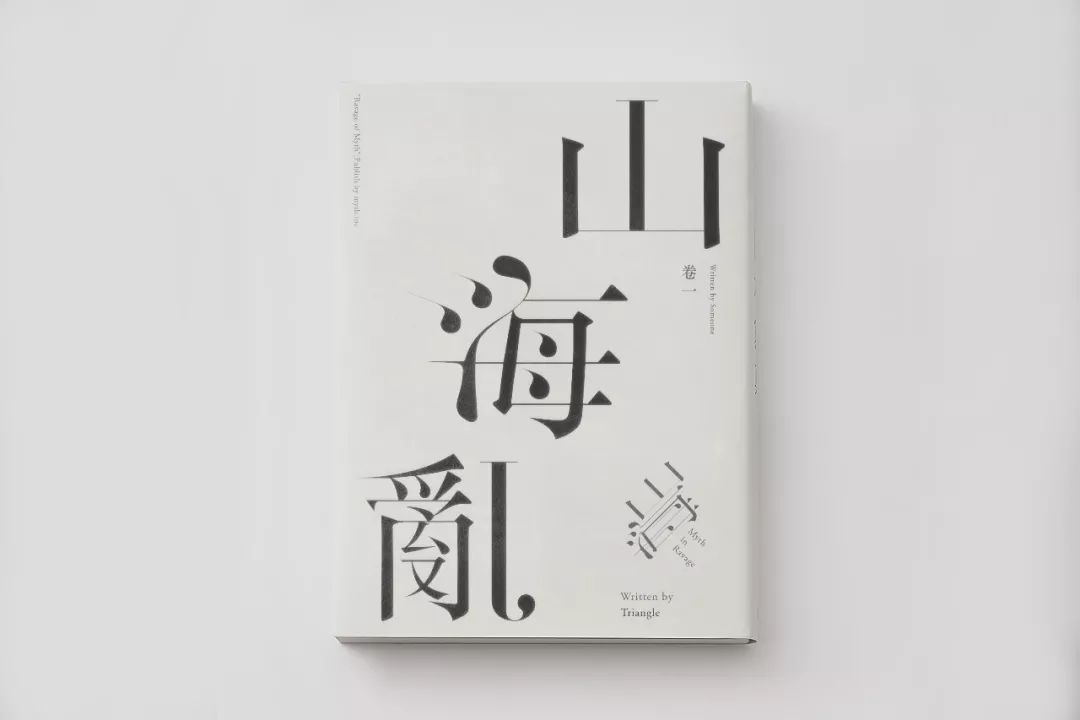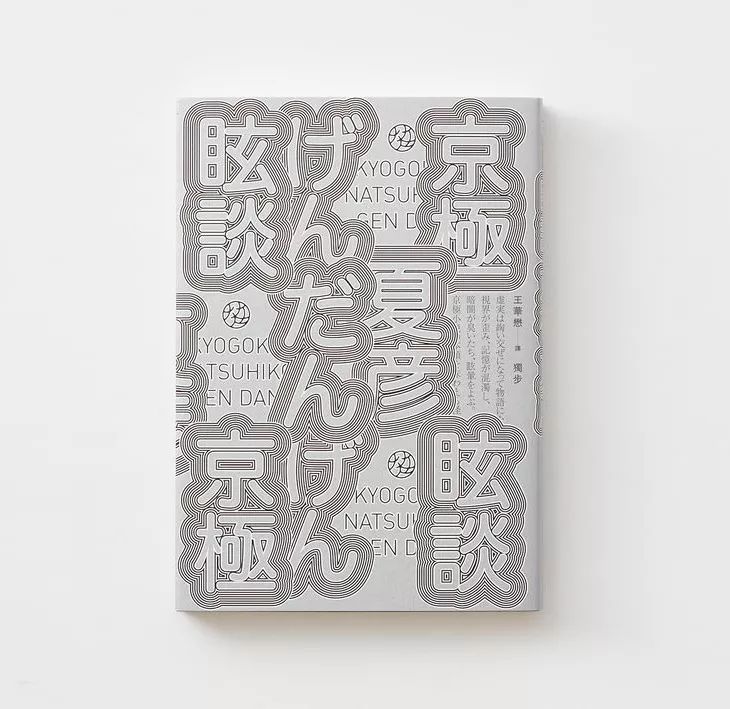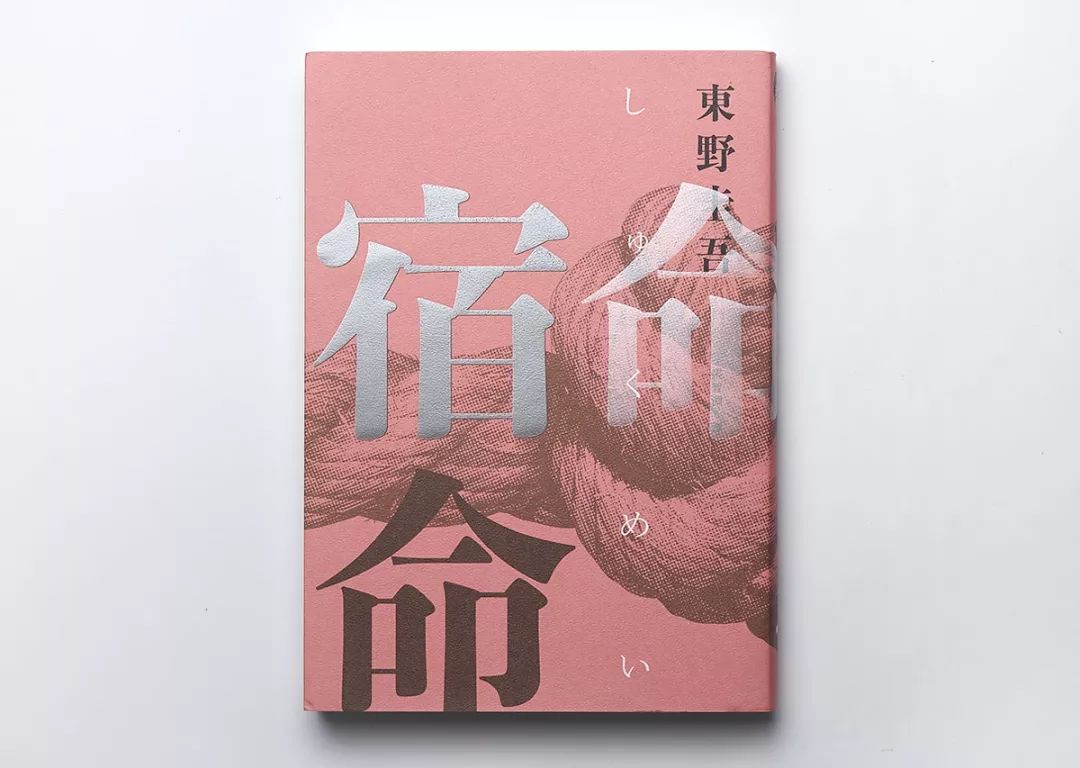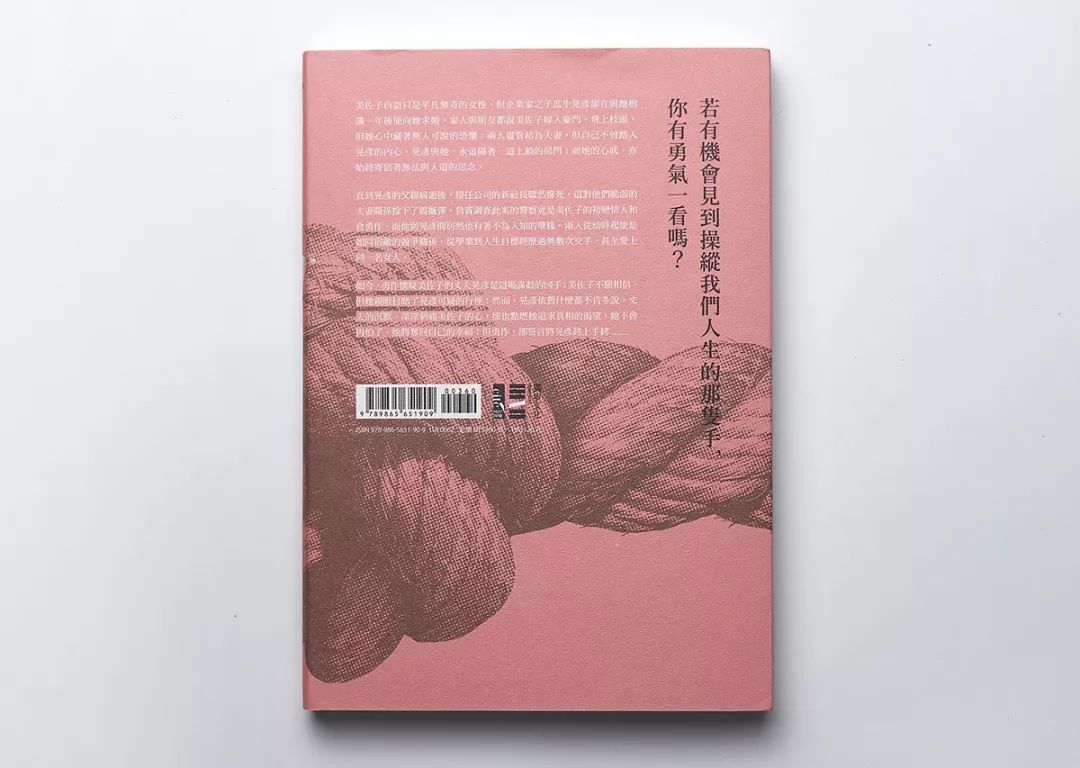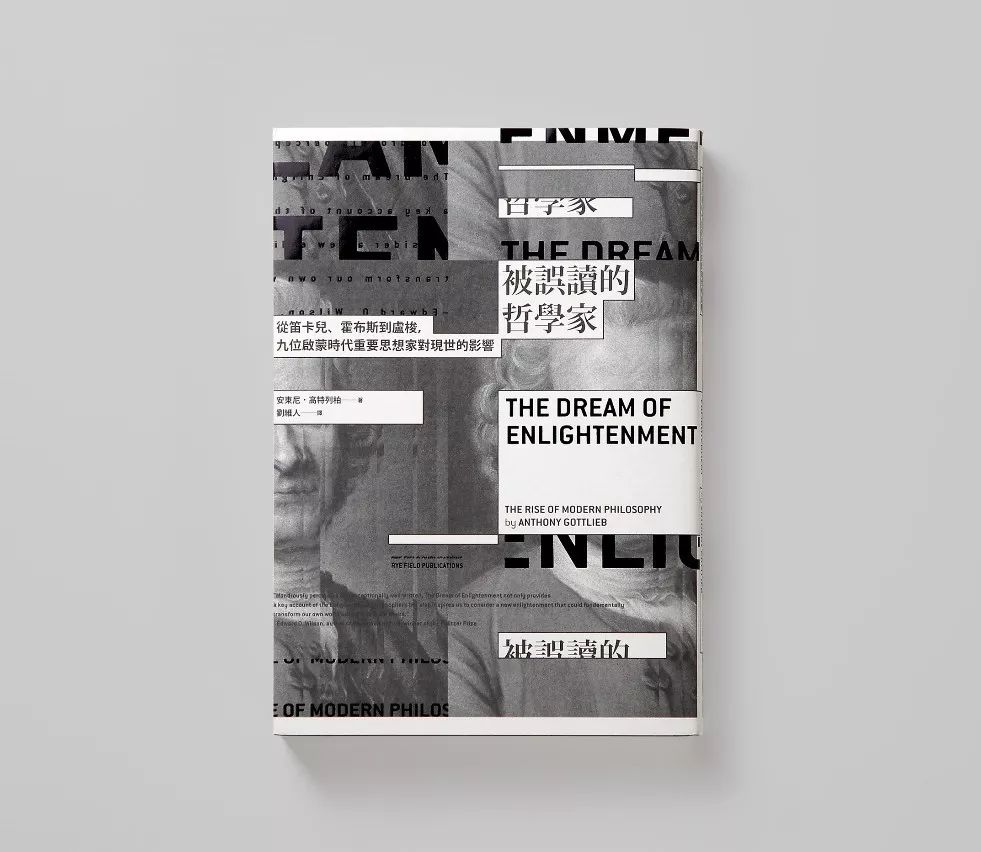
想设计出好的封面,这五大手法能帮到你!
封面设计指画册内容、形式、开本、装订以及印刷后期的综合体现,好的封面设计要从全方位进行考虑。设计者应根据书籍的不同性质、用途和群体,把这三者有机的结合起来。封面的表现形式主要从图像、文字、材质工艺等方面进行设计,打造出主次分明、简而不空的视觉效果。最后需要注意封面的风格要与内页达到统一。以下为大家总结出五种常用的封面设计手法:
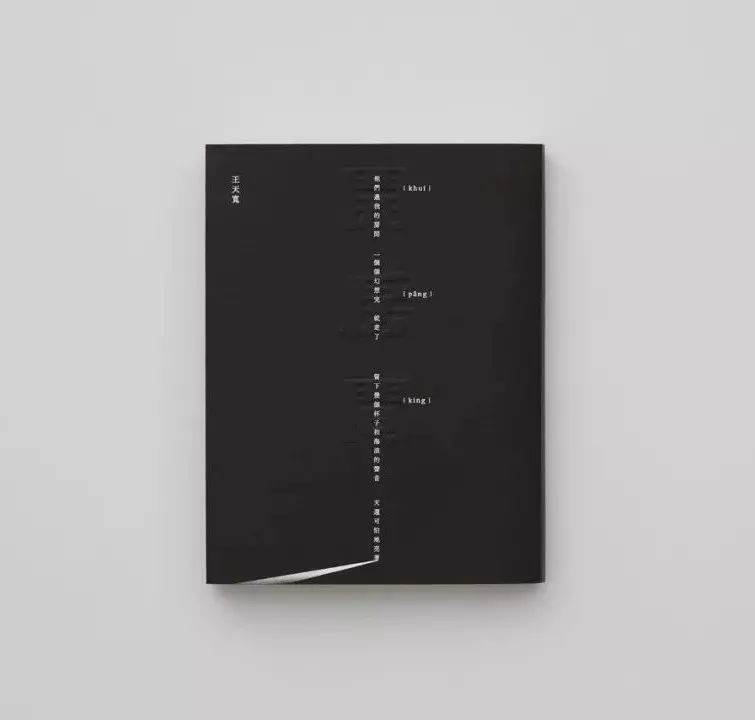
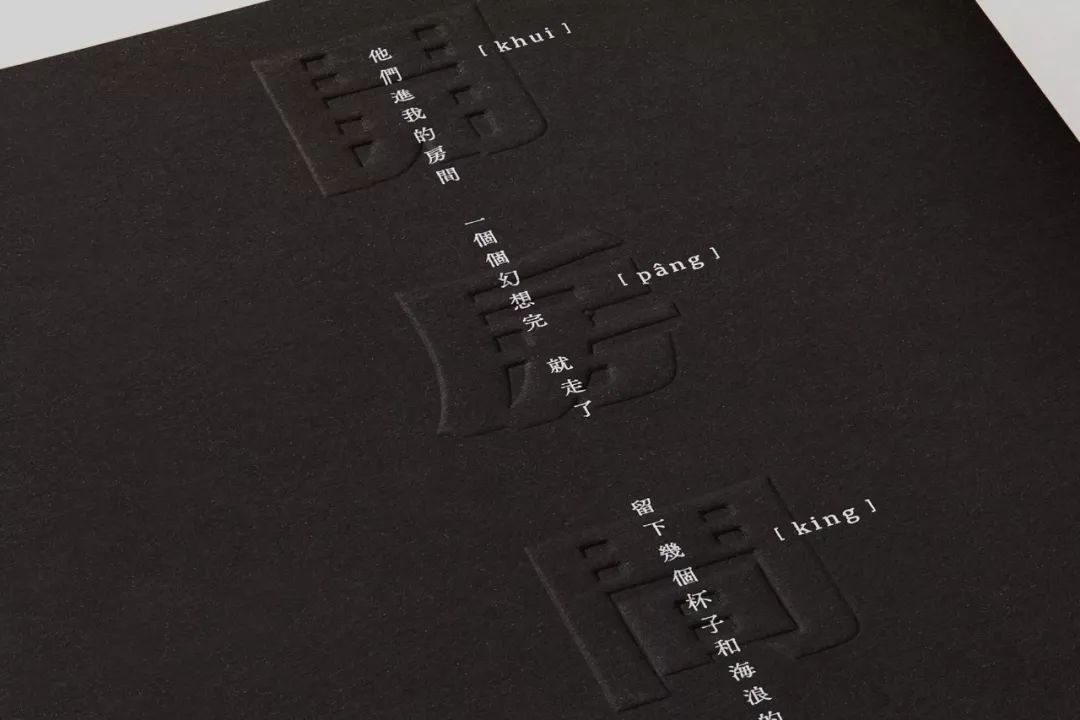
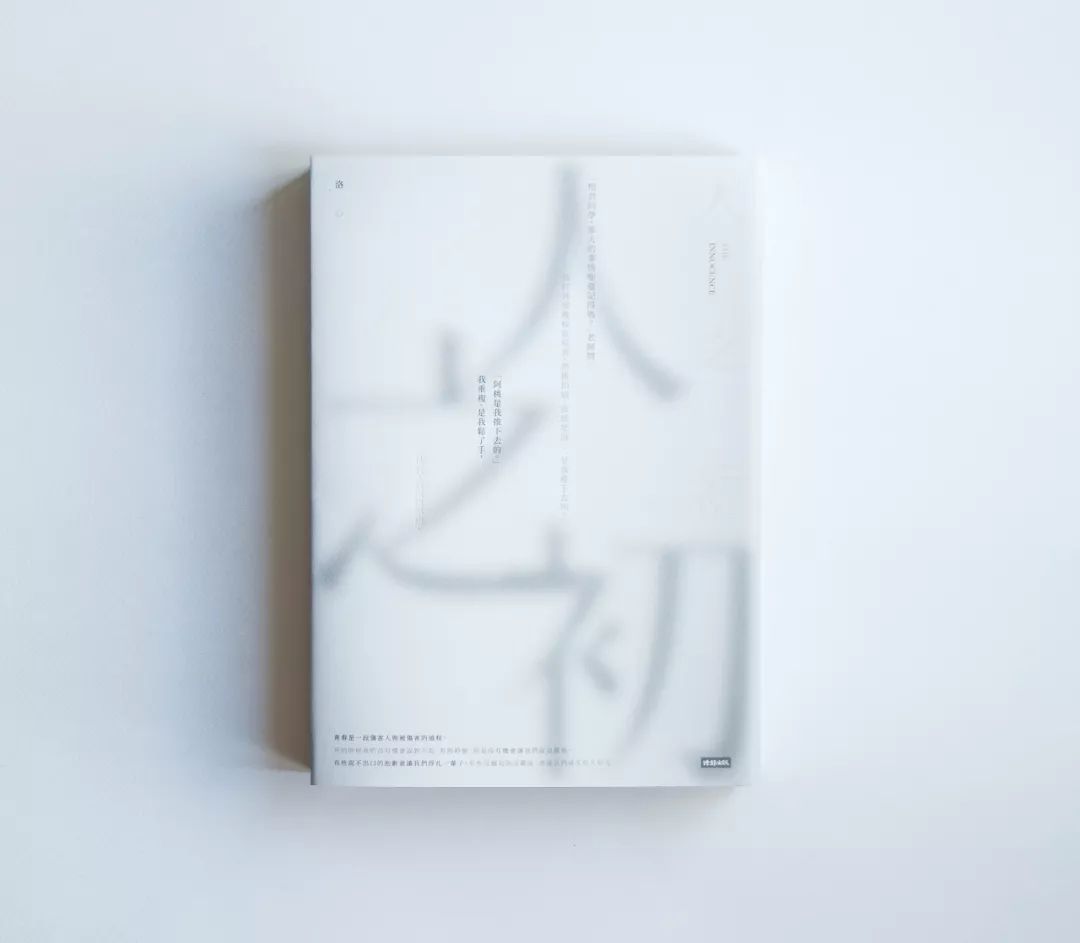
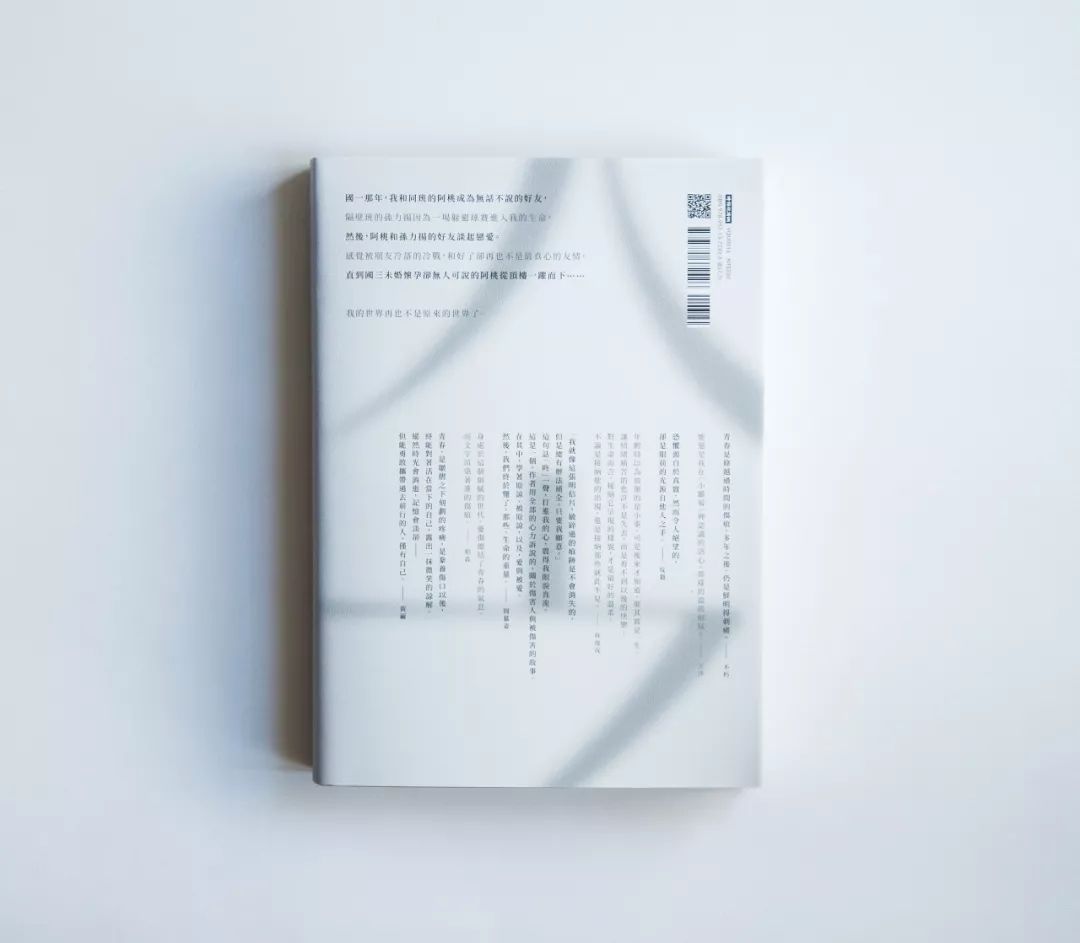
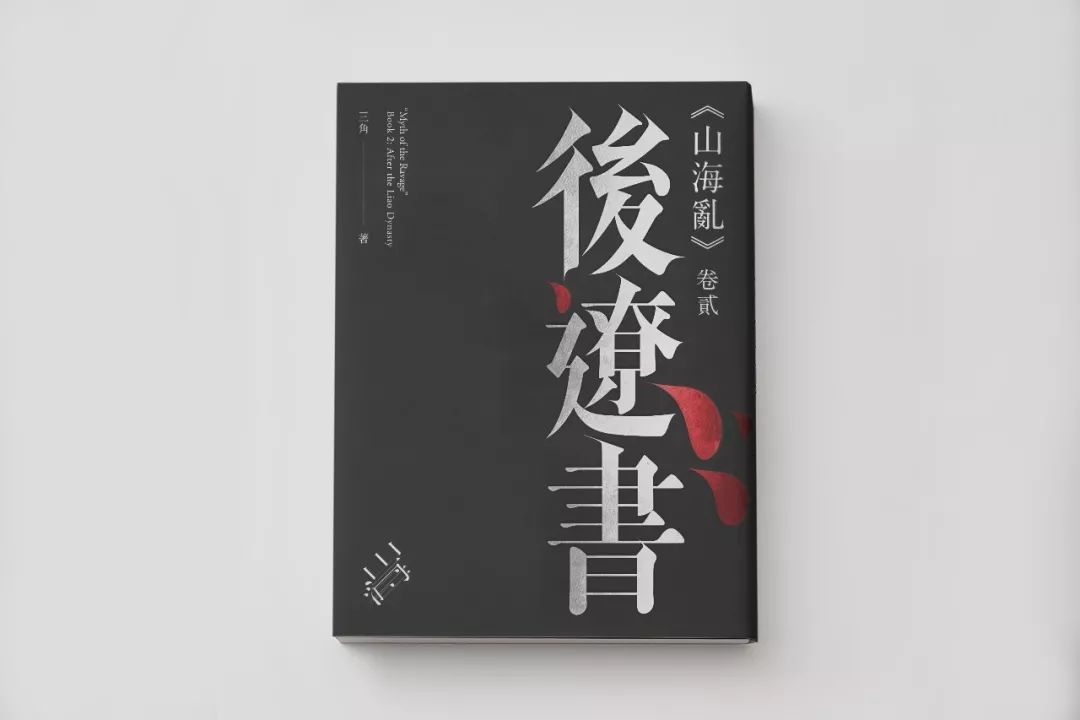01#纯文字编排
利用文字作为封面元素,能直接表达整本书的主题。字体一般会经过重新设计,以独特的形象展现。这种方式适合用于各种行业的封面设计。编排时要注意文字间层级关系,灵活运用对比关系来提升画面的层次感,另外还可以添加线条来辅助排版,增强设计感和精致感。
02#文字+图像编排
在封面中插入与内容或品牌调性相匹配的摄影图片,来突出主题。这样不仅能快速传递宣传信息,还能达到强烈的视觉效果。如果只使用一张图片,通常的处理方式是让图片占比较大的版面空间,提高图版率。图片多数以出血形式或去底图展示。
# 图像满铺编排 #
# 图像三边出血编排 #
# 图像去底图编排 #
# 图像在版心内编排 #
03#文字+图形编排
封面加入图形的设计,能提升画面的艺术感和形式感。比如某些主题无法用具象的图来传达概念,那么可以设计抽象的图形来表达。将图形当成封面的主体,让设计更有内涵和细节。需要注意图形必须与设计主题有关且具有创意,否则会造成画蛇添足。
04#文字+插画编排
插画形式可以理解为经过手绘处理的图形。插画的好处在于它具有丰富的想象力和自由创造性。
05#文字+色块编排
当画面出现空洞或单调时,且在没有其他素材添加的情况下,增大上色面积是一种花最少的时间来提高版面率的方式,以增加画面丰富性。如果想让画面具有层次性,色块与背景之间的颜色形成对比,起到聚焦、突出的作用。
最后,不要忘记印刷工艺。为了增加封面的美观性,会添加一些印刷工艺、特殊纸质,比如UV、烫金、凹凸、丝印、覆膜、镂空等工艺。即便是简单的烫金银也能给封面带来精致感。